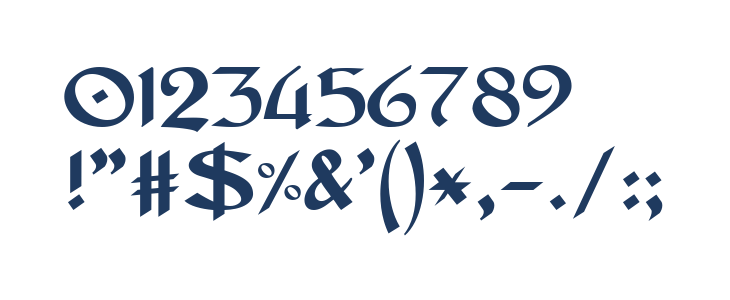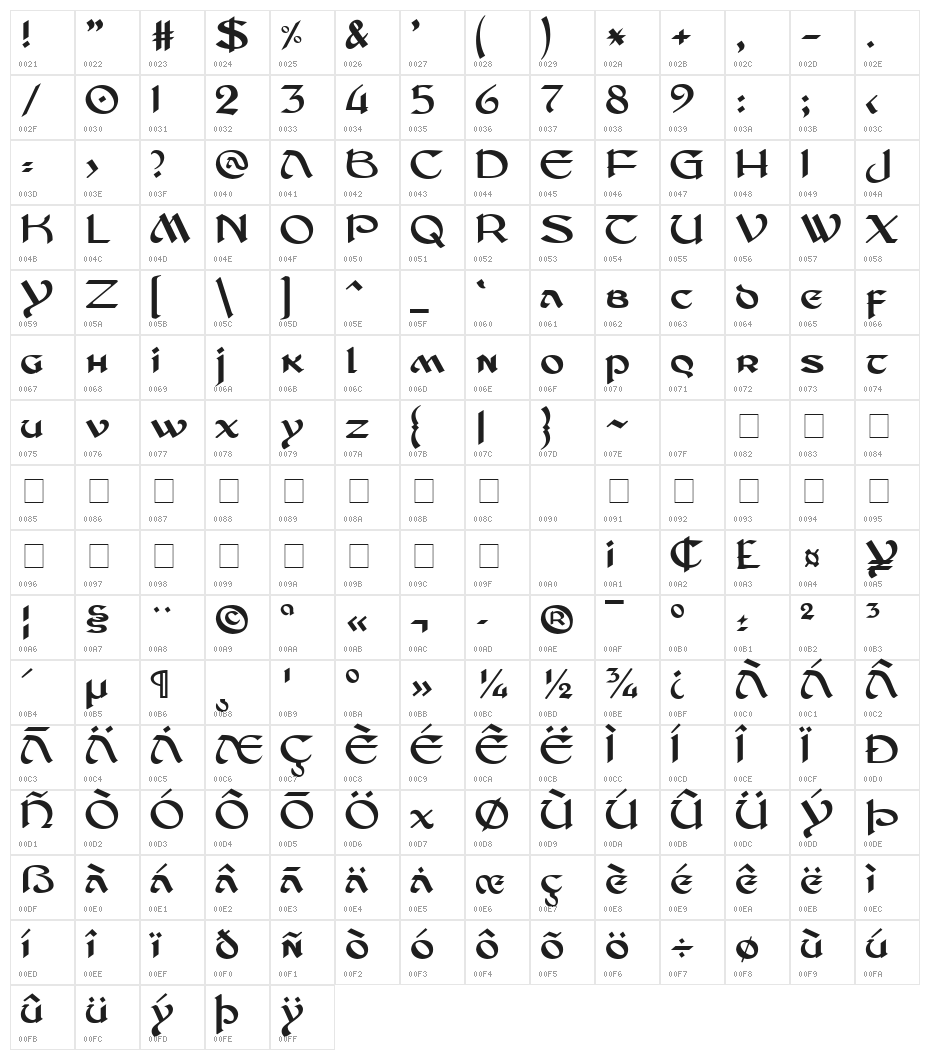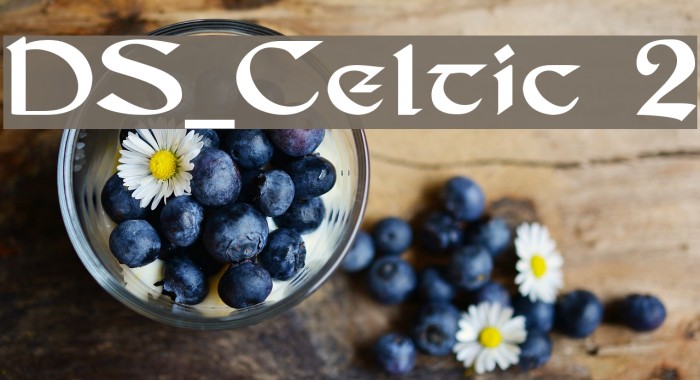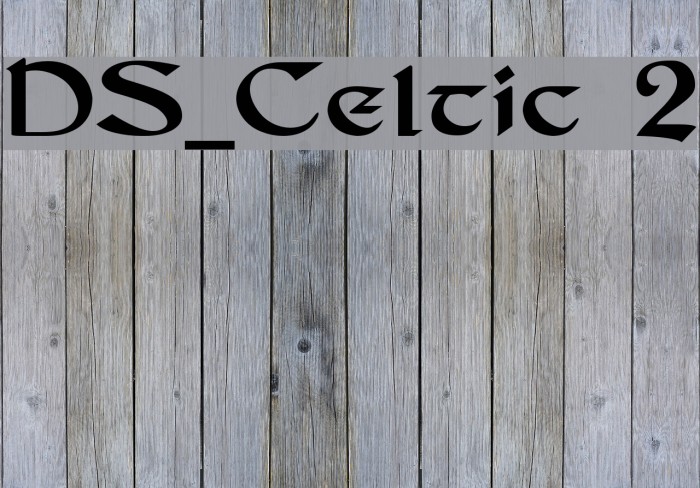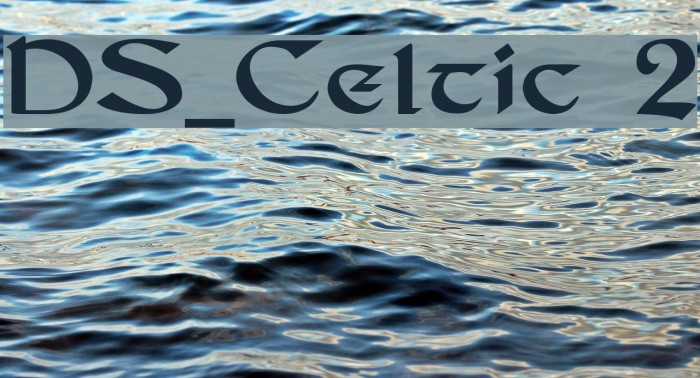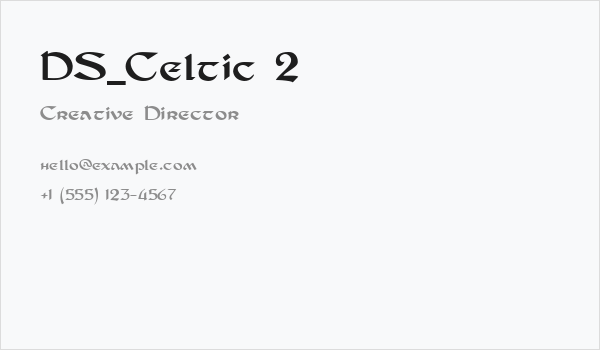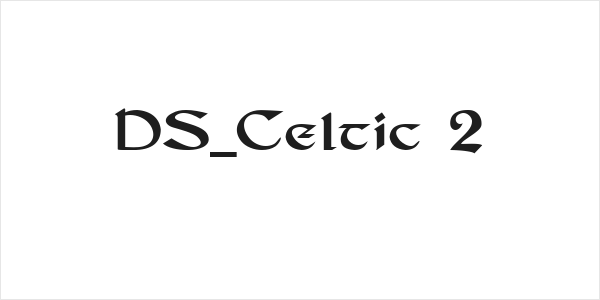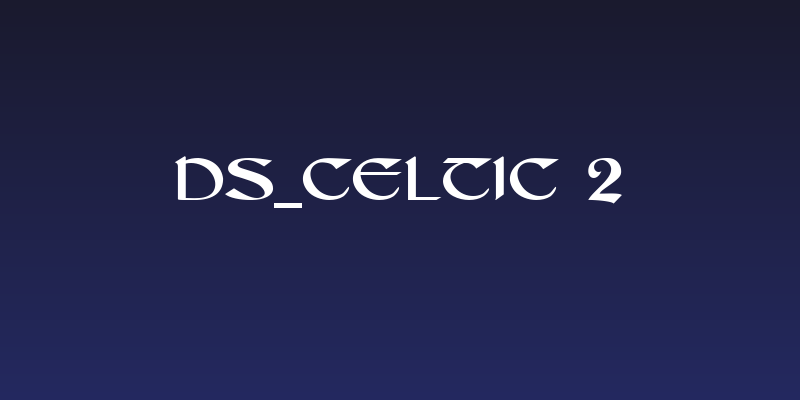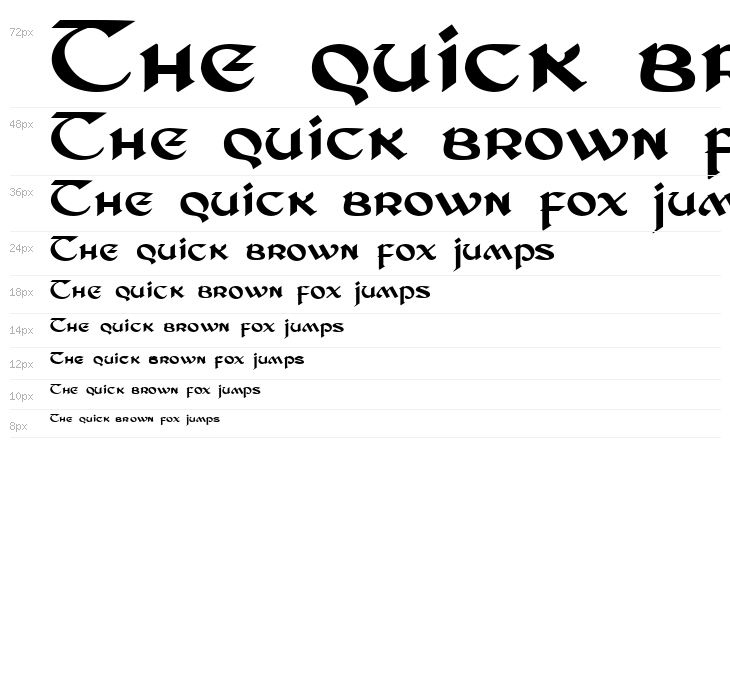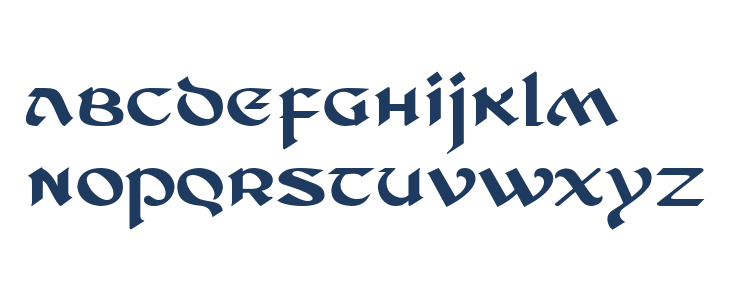
DS_Celtic 2 Font
| Proiecte propuse | Ideal for historical or fantasy-themed projects, book covers, posters, and branding that requires a touch of ancient elegance. |